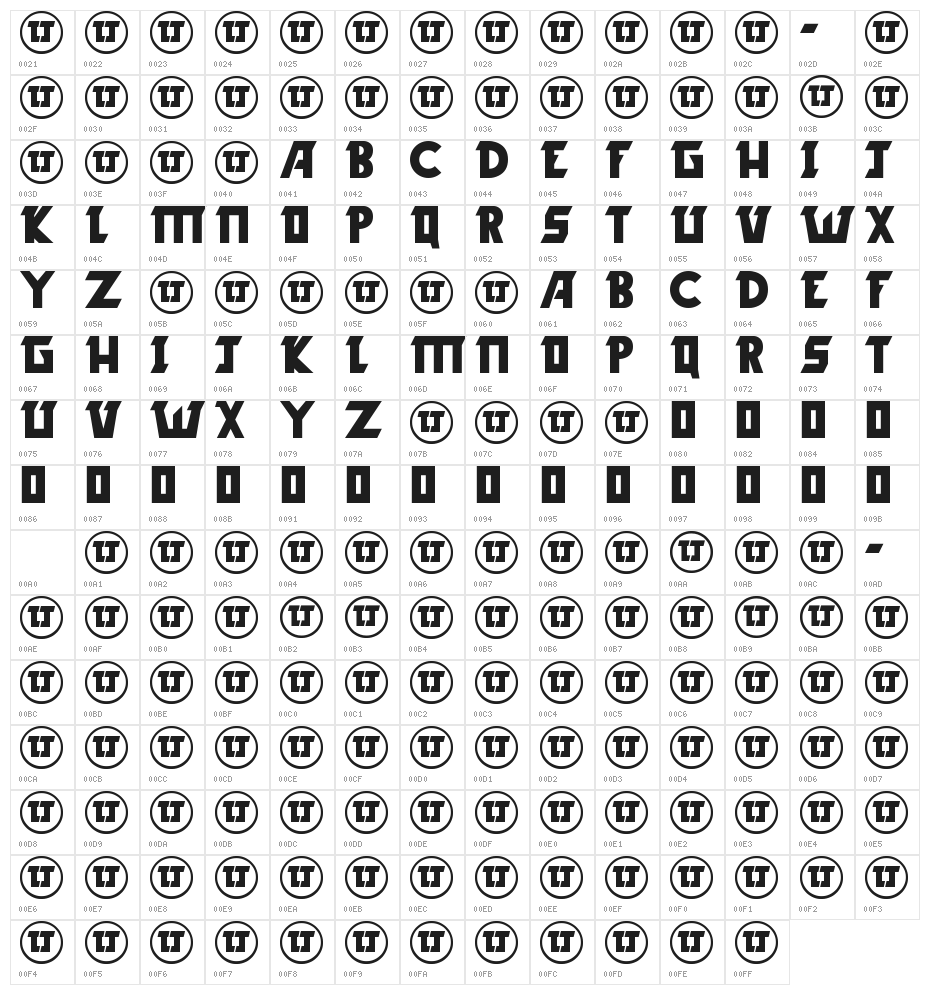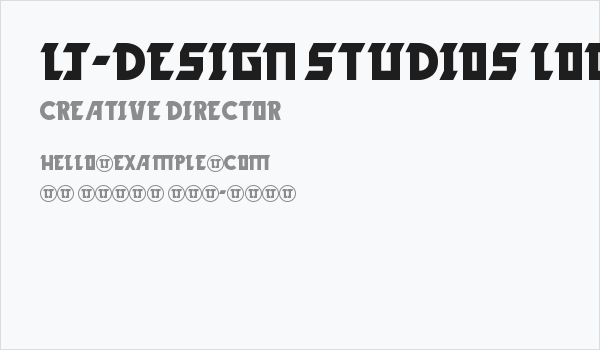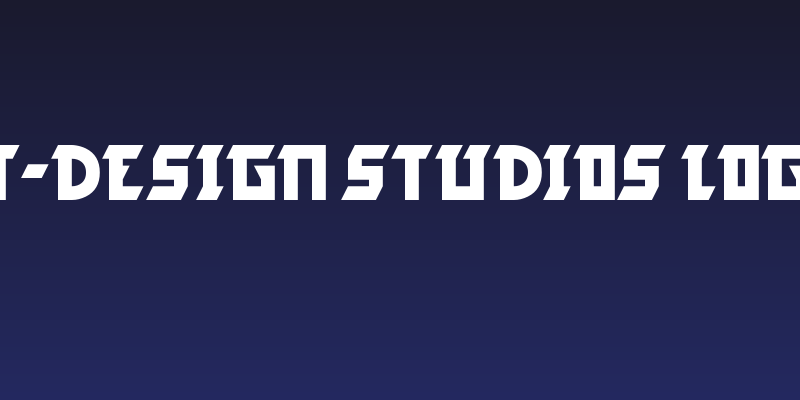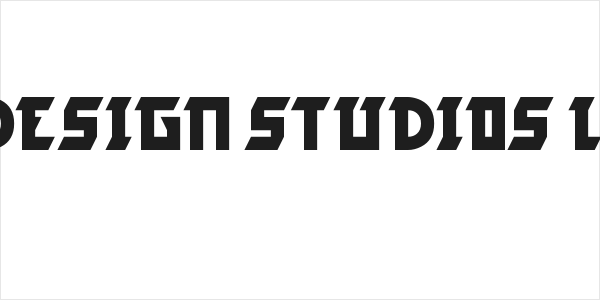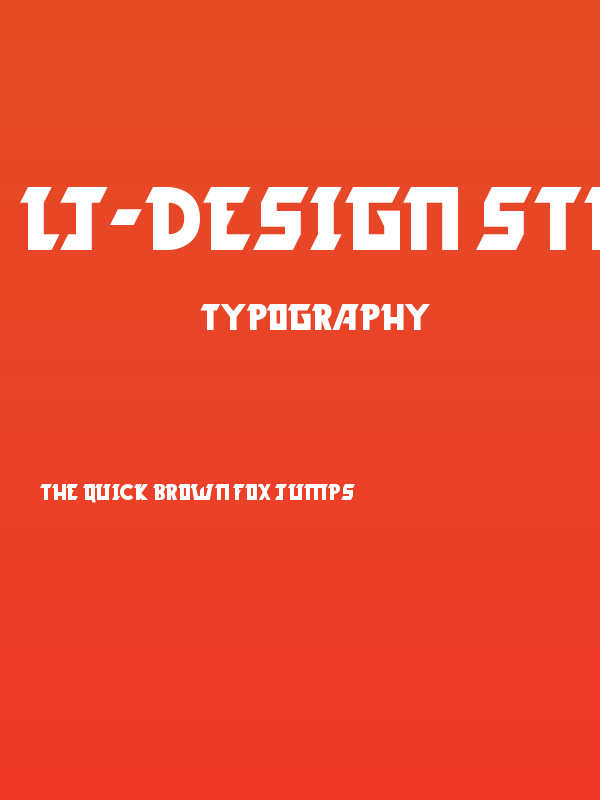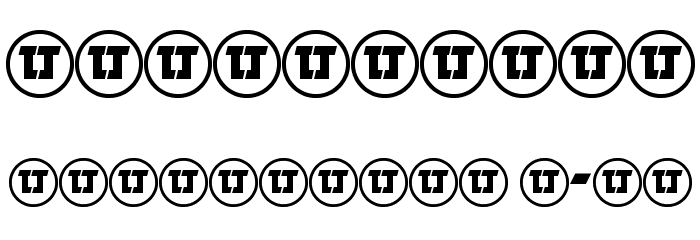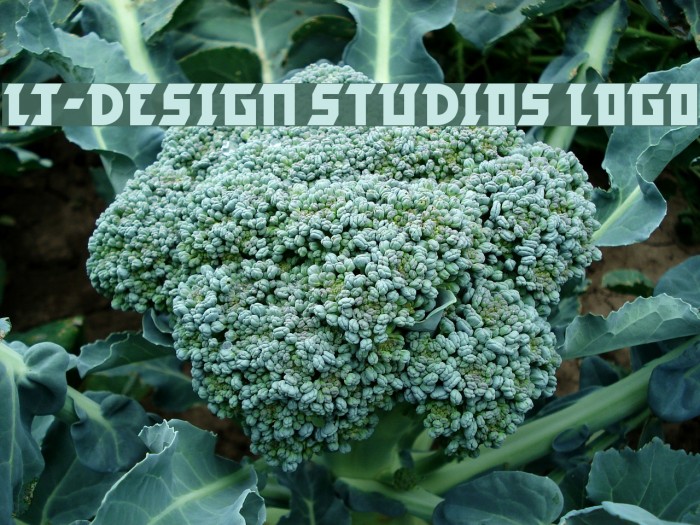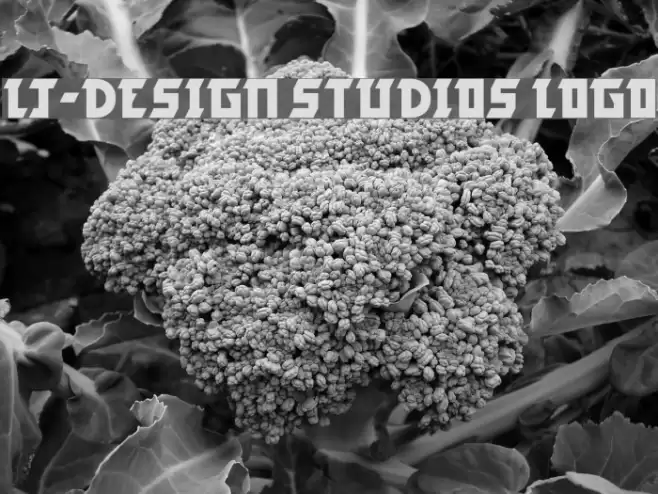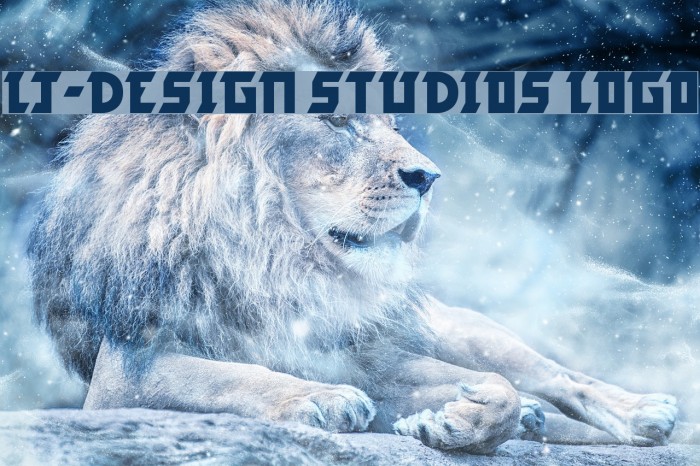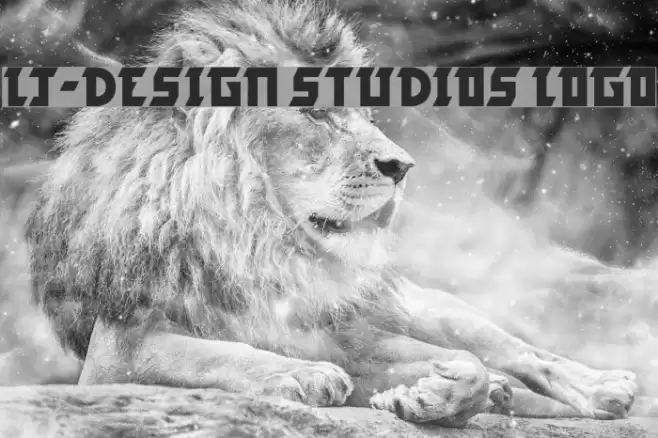
LJ-Design Studios Logo Font
| Рекомендуемые проекты | Ideal for logos, headlines, posters, and branding materials that require a strong, modern look. |